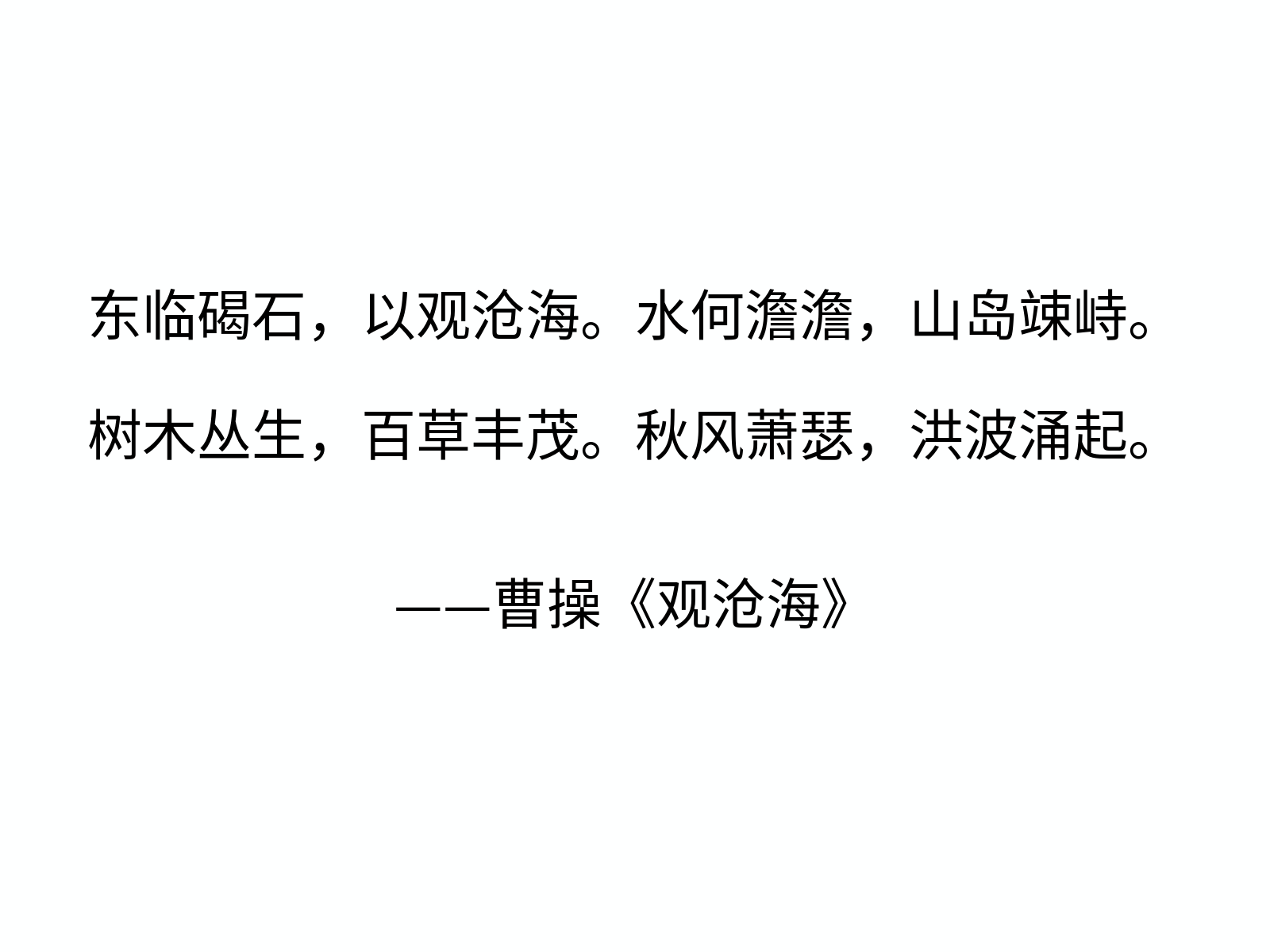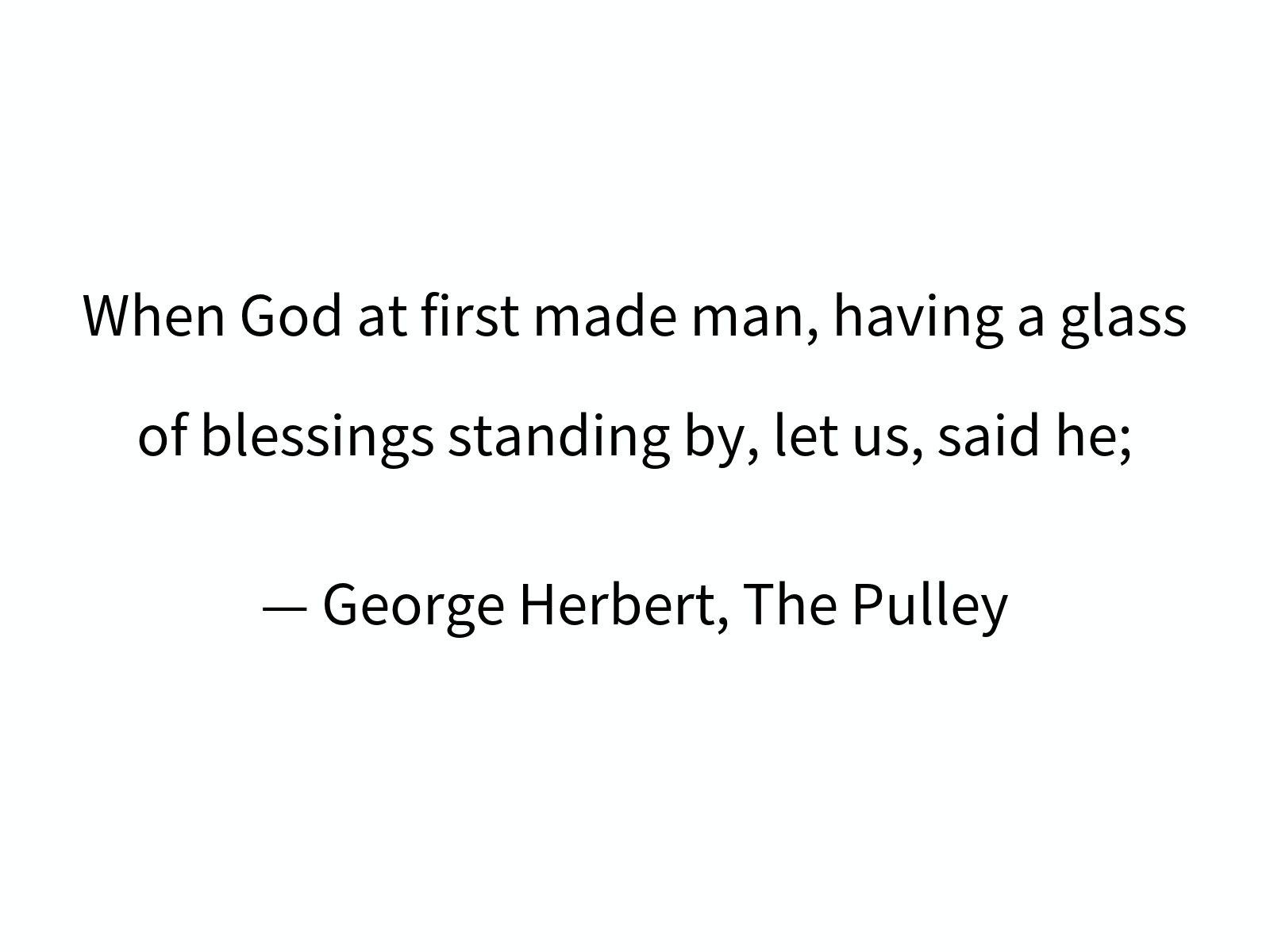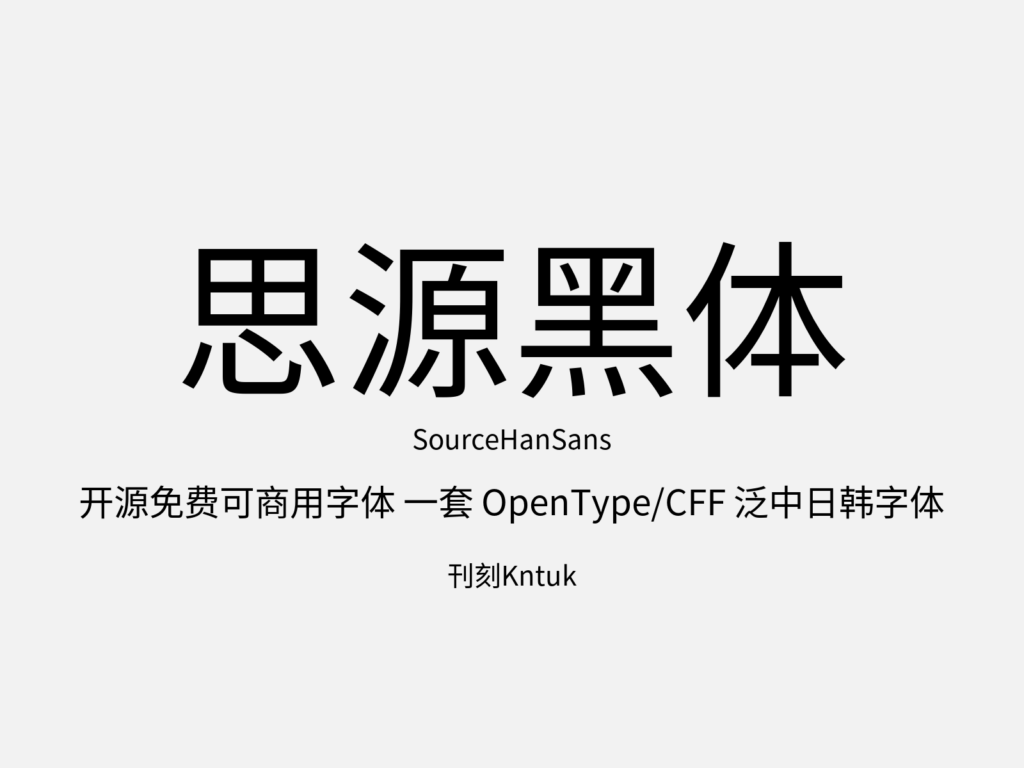
思源黑体(Source Han Sans)是由Adobe与Google联合开发的开源字体,专为全球用户提供卓越的中文字体解决方案。它支持简体中文、繁体中文、日文、韩文以及拉丁字母,提供了从ExtraLight到Heavy的7种字重,拥有超过6.5万个字符,满足多语言混排的需求。字体设计将传统与现代元素完美融合,笔画简洁、结构统一,能够适应各种设备和分辨率,兼顾阅读的舒适度和视觉美观。其开源特性(SIL OFL协议)允许自由商用及修改,被广泛应用于网页设计、移动应用、出版印刷和品牌标识等领域。作为跨平台的通用字体,思源黑体显著提升了文本的可读性和一致性,成为数字化时代中文字体设计的典范,具备高度的实用性和开放性,促进了全球信息交流的便捷与高效。